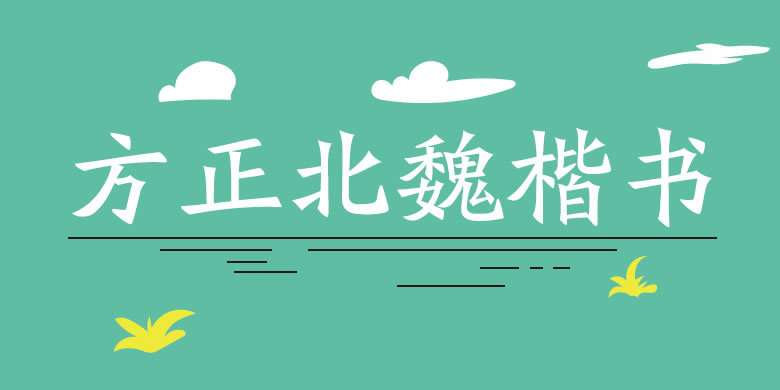
方正北魏楷书繁体
品牌:方正字库设计师:朱志伟发行时间:2003字库编码:大陆简体(GB2312-80)、大陆繁体(GB12345-90)、简繁扩展(GBK)、港台地区(BIG-5)分类:楷体
方正北魏楷书繁体
方正北魏楷书的设计源于北魏墓志、造像中的方笔。设计师巧妙地将北魏时期书法艺术的特色融入到现代排版字体中。横竖笔画挺拔刚健,撇捺飘逸灵动,钩和点画严整饱满。笔画的起笔和折笔处斩钉截铁,如刀削玉,给人以沉着痛快之感。除了适用于杂志和书籍的正文排版,还可用于广告标语。